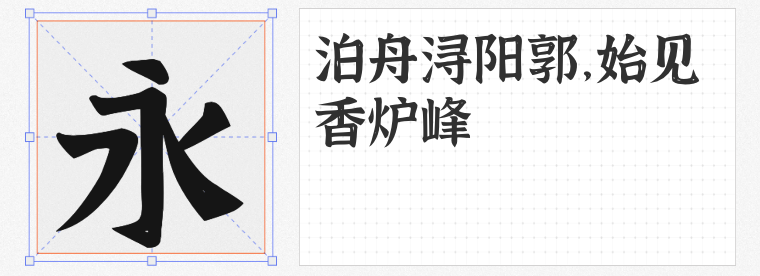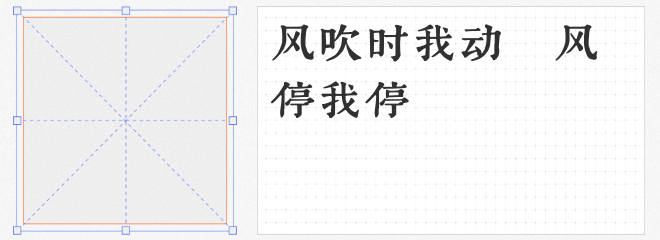
四款免费商用字体赋能东方美学设计
在古风设计中,字体不仅是信息传递的载体,更是传递文化意境的视觉符号。若想以笔墨勾勒山水意境,以线条演绎传统风韵,以下四款免费商用的古风字体堪称设计师的“文房四宝”,既能彰显文化底蕴,又能灵活适配多元场景。
1.【寒蝉书体·春秋 秋鸿】
取意“蝉鸣春秋”的雅致,这款楷体以流畅笔意还原古籍风骨。其字形舒展如流水,横竖转折间自带文人书斋的沉静气质,既适合古籍复刻类设计的标题点睛,又能为现代文案增添一抹水墨意趣。开源基因赋予其极高的拓展性,无论是诗词排版还是品牌标语,都能传递“笔落惊风雨”的东方诗意。
2.【润植家刻本简体】
若需兼顾刻本的遒劲与手书的温润,此字体堪称首选。在刀刻的棱角中融入毛笔的柔韧,横画如玉箸垂露,竖笔似铁画银钩,既保留传统刻本的古朴韵味,又通过弧度处理削弱了生硬感。从书籍扉页到文创包装,从横排正文到竖排题跋,均能展现“刚柔并济”的东方美学哲学。
3.【江西拙楷】
这款字体以“拙”破“巧”,刻意保留书写时的自然颤动与墨色飞白。笔画或粗或细,结构时松时紧,恰似文人即兴挥毫的率真。看似“不规范”的笔触,实则暗含“大巧若拙”的哲学,尤其适合茶酒包装、手作品牌等追求返璞归真之美的场景,让设计自带“人间烟火气”。
4.【鸿雷板书简体】
源自书法练习时的灵光乍现,这款手写体兼具碑帖的骨力与行草的洒脱。字形时而如惊雷裂帛,时而似春雨润物,将练习时的犹豫、顿悟、沉淀凝结为独特的艺术语言。适用于音乐专辑封面、艺术展览标题等需要强烈个人风格表达的场景,让设计作品拥有“笔迹即心迹”的温度。